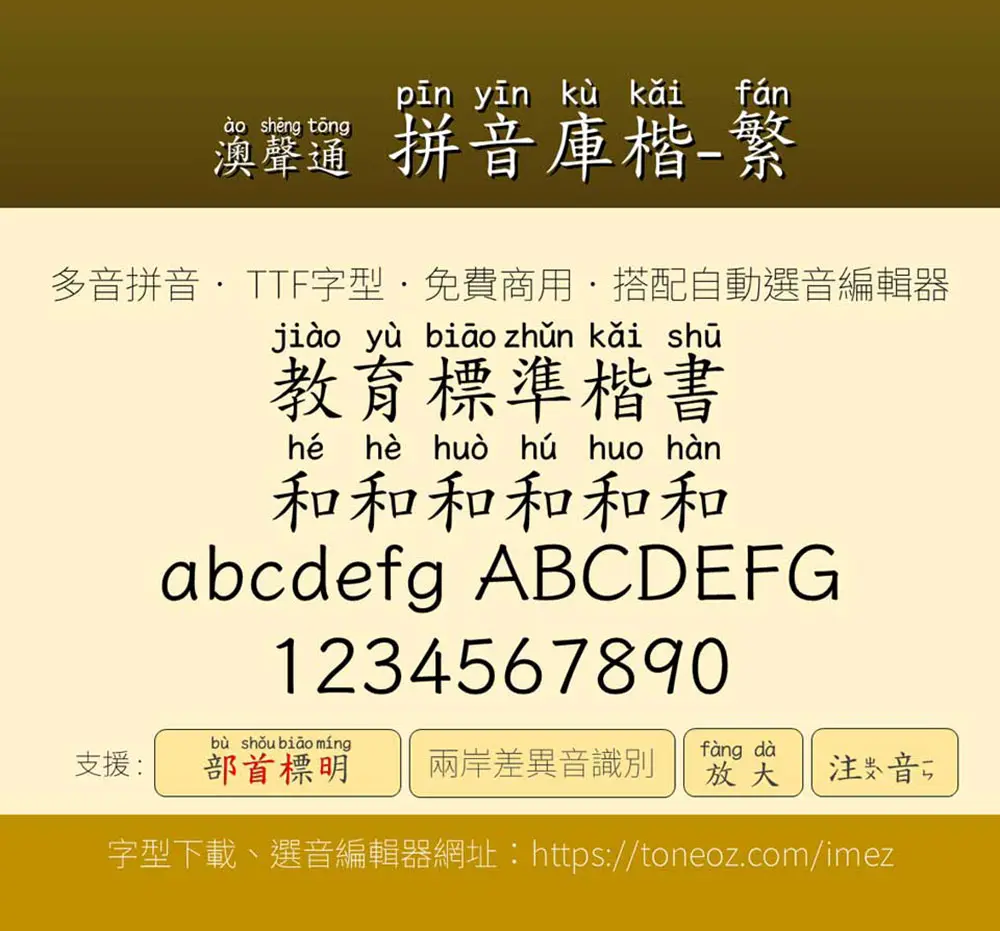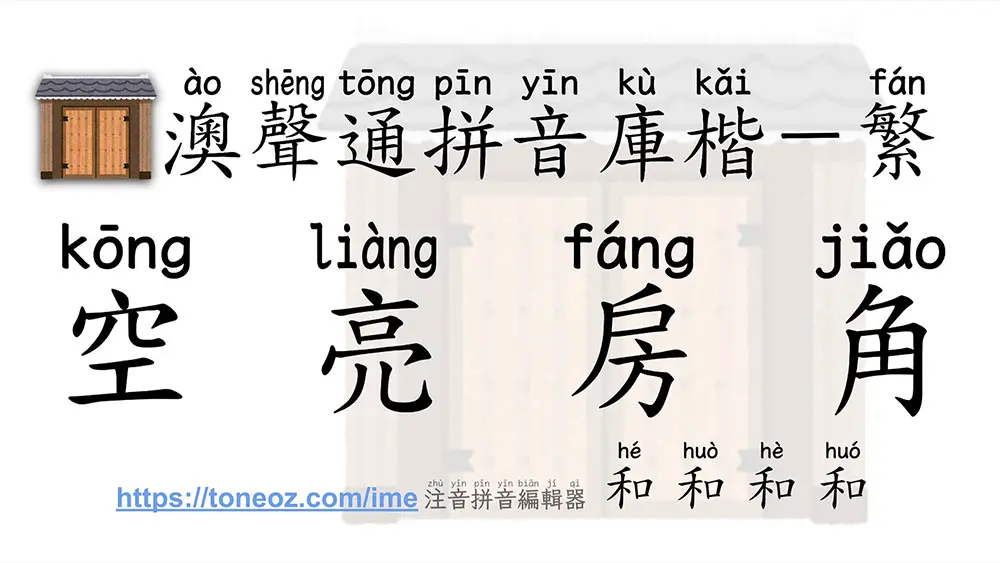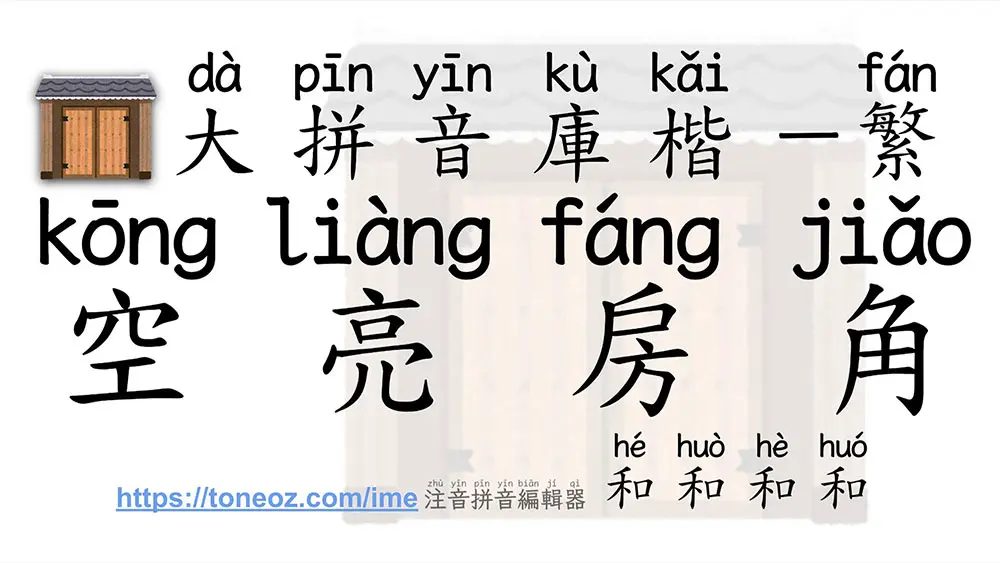
澳聲通拼音庫楷是一款基於全字庫正楷體的可選多音字的TrueType楷體拼音字型,滿足中文現場教學需求,搭配國際標準《ISO 7098中文羅馬字母拼寫法》的漢語拼音字型,適合熟悉羅馬字母的學習人士。
標準版(小拼音版)的大小適當不影響字距,適合文章閱讀或試卷,大拼音版本適合投影片或標題。每個字的拼音寬度不同,最短的只有一個字母,最長的字「裝zhuāng」有6個字母,大拼音字型的拼音此時可能會重疊,使用者可利用字距或者加入空白來調整。
一、澳聲通小拼音庫楷(ToneOZ-Pinyin-Kai-Traditional)